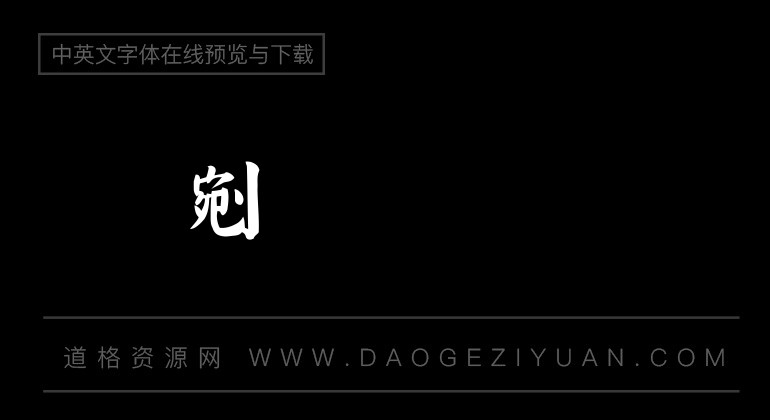
金梅毛楷体
金梅毛楷体是一款经典的毛笔字体,它是一种中国传统毛笔字体,也是中国传统文化的象征。金梅毛楷体字体的特点是笔画流畅、结构紧凑,笔画粗细均匀,笔画粗细变化较大,曲线圆滑,结构清晰,比较节省空间,使用范围广泛。金梅毛楷体字体常用于书法、绘画、拼音字体、印刷、广告等领域。
金梅毛楷体是一款非常不错的手写艺术字体,具有很好的视觉感,适合于文化类的宣传设计、商业类品牌的广告和产品包装设计以及个性化文字排版等较多场景。